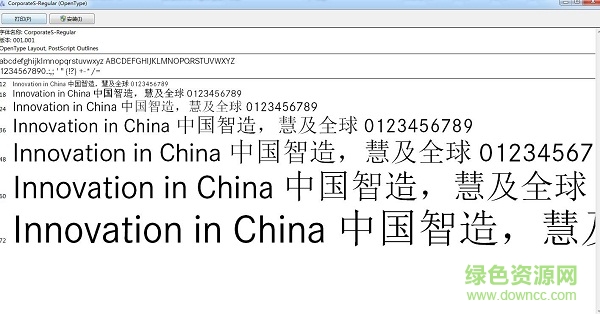
字體樣式regular字體是AE視頻軟件中的一款常規(guī)英文字體,筆畫單純,結(jié)構(gòu)平穩(wěn),整體干凈流暢,不粗也不細(xì),給人的視覺感受比較舒服,歡迎大家免費(fèi)下載!
字體的粗細(xì),英文用Weight一詞表示,越粗的字Weight就越“重”;的各種具體表示方法從細(xì)到粗一般有:Light、Regular、Bold、 Extra Bold、Black等;不過這些表示法并沒有統(tǒng)一的標(biāo)準(zhǔn),而且各Weight之間的比例關(guān)系亦因字體而異。